Seleccionar la tipografía adecuada es un paso importante en la definición del tono de voz de tu diseño. Por este motivo, el especialista Álvaro Franca ve en las fuentes tipográficas infinitas posibilidades de comunicación y expresión, ya sea como diseñador en el estudio Vasava, en Barcelona, o como cofundador de Naipe Foundry, donde colabora con clientes como TV Globo, Sony Music y Descomplica.
En este curso, Álvaro te enseñará a seleccionar la tipografía adecuada para pequeños y grandes proyectos, desde un logotipo hasta el diseño de una revista. Conocerás la historia de la tipografía y descubrirás cómo combinar familias, tamaños y estilos de fuentes para crear una pieza eficaz y coherente. Al final del curso, tendrás la confianza necesaria para seleccionar y acertar en pleno con la elección de tu fuente, sea cual sea tu proyecto de diseño.
Empezarás conociendo a Álvaro Franca, que te hablará de su trayectoria en el mundo del diseño, de sus principales referencias y de las fuentes de inspiración para su trabajo. Después, te contará cuál es el contenido del curso y el proyecto que realizarás como ejercicio final.
El siguiente paso será preparar un proyecto tipográfico y aprenderás a buscar fuentes y a encontrar materiales sin hacer grandes inversiones. También verás que cada formato de fuente tiene una función distinta y estudiarás las licencias de uso, fundamentales para trabajar con tipografías.
A continuación, verás la importancia de conocer a fondo las letras y cada miembro de la familia tipográfica. Aprenderás la historia del alfabeto latino, descubrirás el origen de las letras mayúsculas y minúsculas o por qué las cursivas son inclinadas, y aprenderás más sobre el concepto de jerarquía textual: cómo organizar las fuentes de forma armoniosa para facilitar su lectura.
«Las letras utilizadas a lo largo de la historia de la humanidad absorben y reflejan el espíritu de su tiempo». En esta línea, comprenderás la trayectoria de la tipografía y cómo esta se refleja en los proyectos de diseño. Álvaro te explicará cómo identificar las categorías de tipografías de forma rápida y sencilla, y te enseñará su método de elección de tipografías en función de la forma y la función, además de mostrarte cómo controlar el tono visual de tus piezas.
Al final del curso, verás cómo combinar diferentes familias tipográficas y trabajar la jerarquía textual más en profundidad, dos temas que te ayudarán a pensar en el sistema tipográfico de tu proyecto final. Antes de despedirse, el profesor te proporcionará algunos consejos sobre InDesign que facilitarán tus futuros proyectos de tipografía.
Realizarás la selección tipográfica para el diseño de una revista.
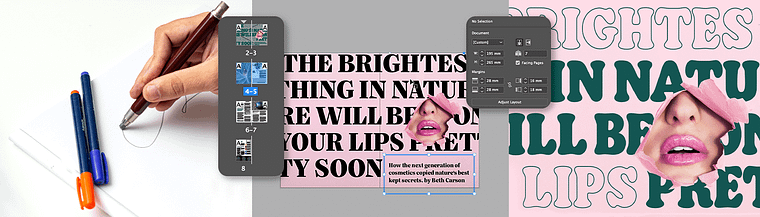
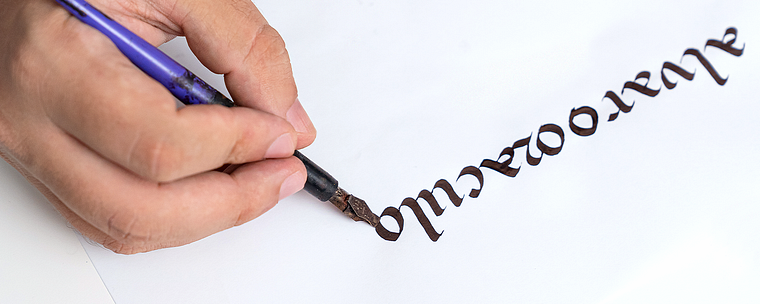
Curso excelente. Uma ótima introdução ao tema, que me apresentou tópicos que eu ainda não conhecia e que, com certeza, vou pesquisar mais.
Very helpful to get a systematic understanding of typography and inspiring to study more.
Introducción
Preparación
Conociendo las fuentes
Historia y clasificación tipográfica
Poniéndolo en práctica: selección de fuentes para una revista
Proyecto final
El curso cubre la historia de la tipografía, clasificación de fuentes, composición visual, creación de fuentes propias, licenciamiento, elección y combinación de fuentes, prácticas del mercado y análisis de proyectos tipográficos.
Se presentan criterios técnicos y estéticos para seleccionar, combinar y jerarquizar tipografías, con ejemplos prácticos en proyectos editoriales, logotipos y carteles.